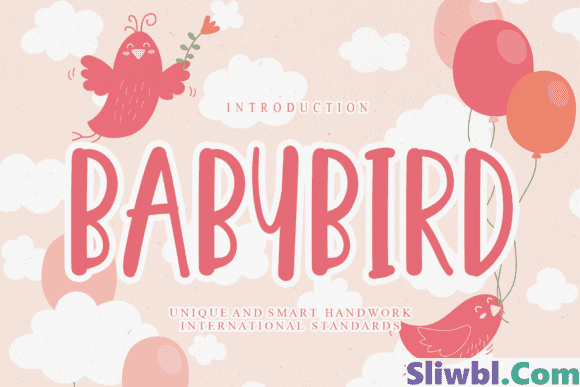
Название: Babybird Font (2021)
Babybird - это милый и веселый шрифт.
Используйте его, чтобы сделать свои идеи еще более реалистичными и создать эффектные дизайны!